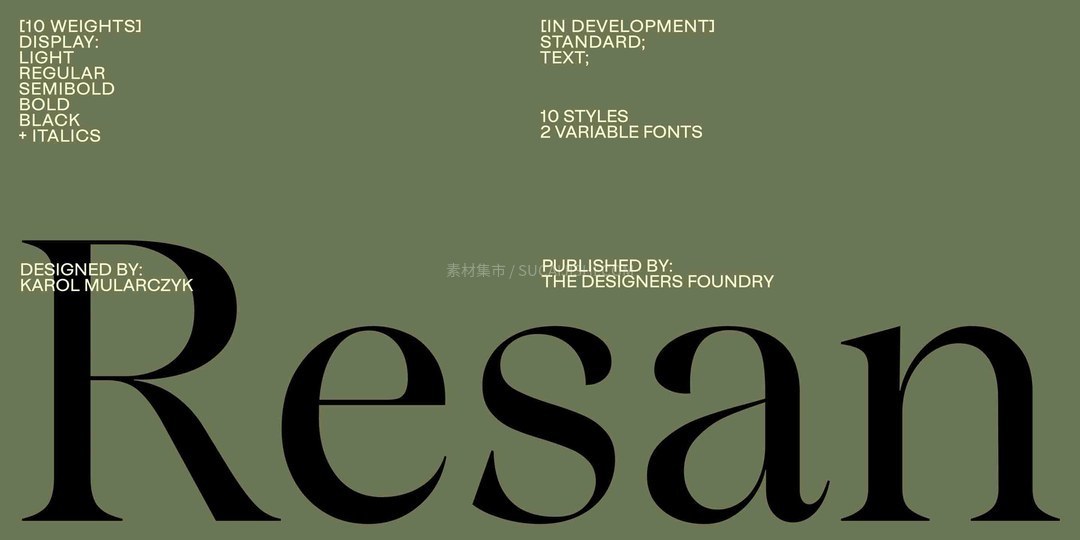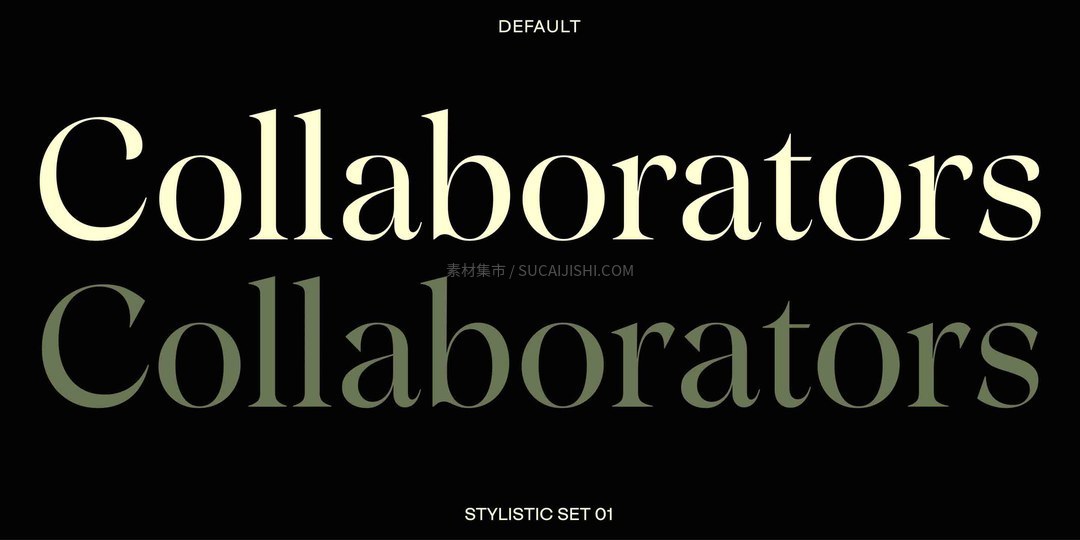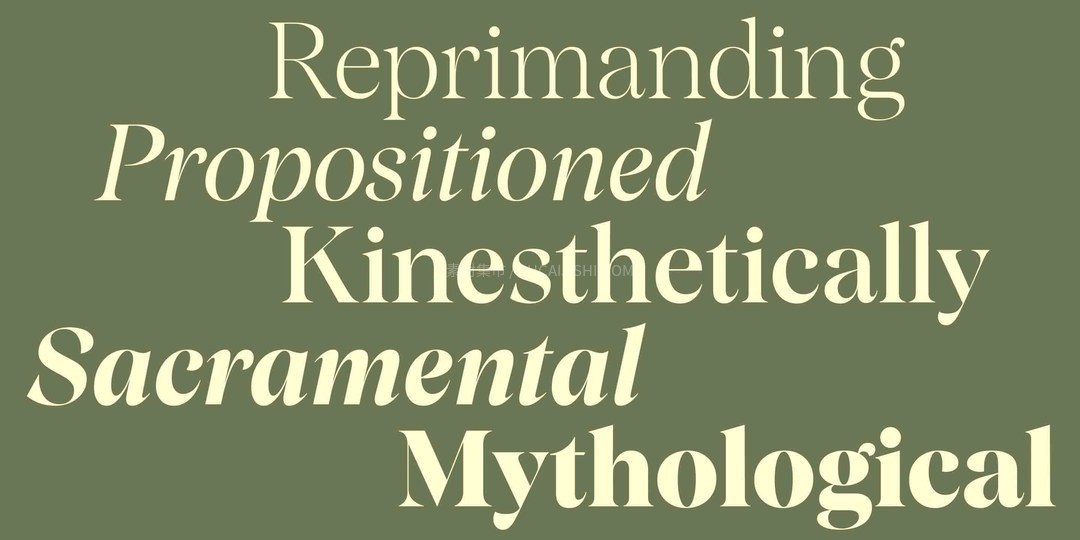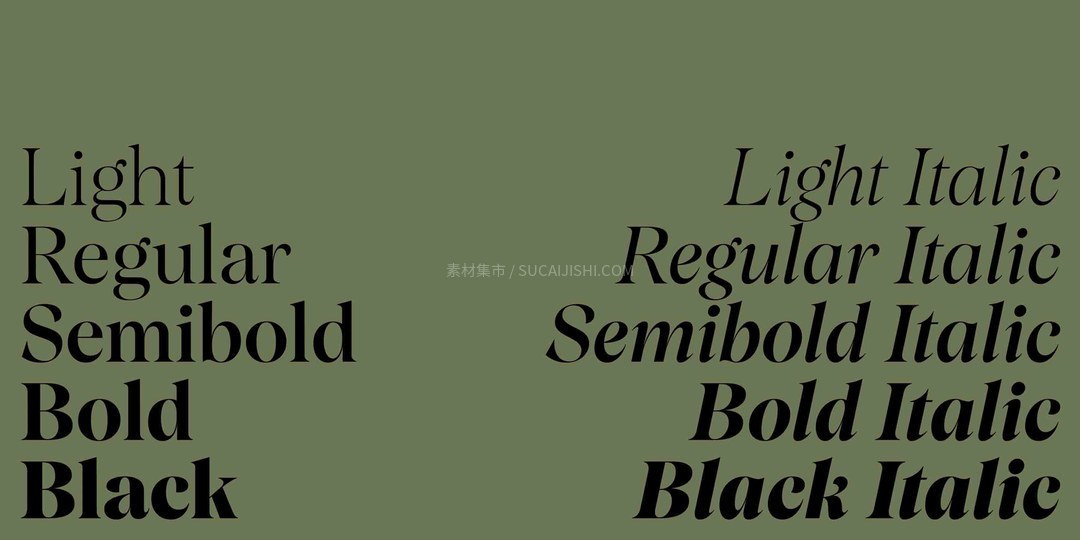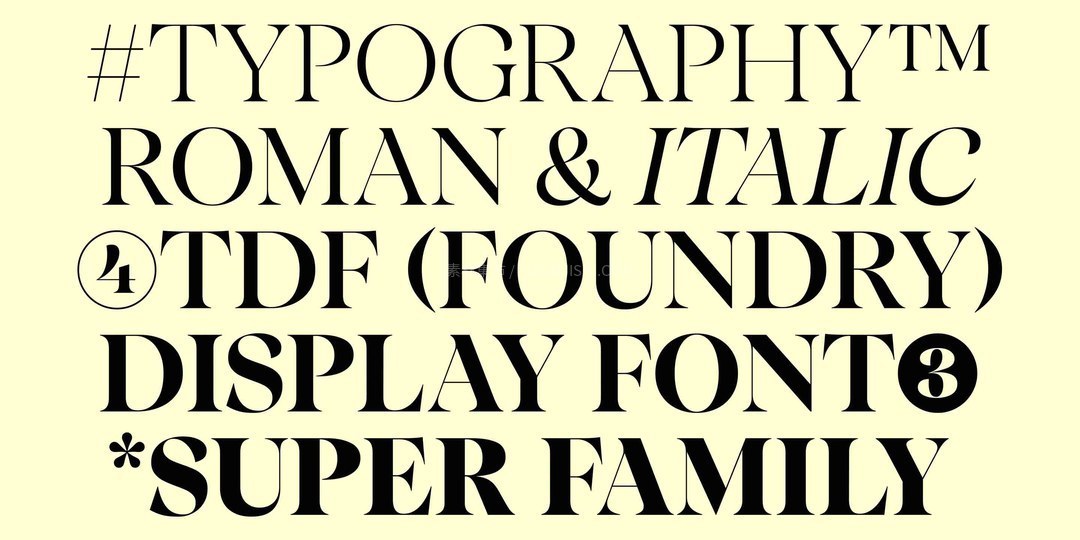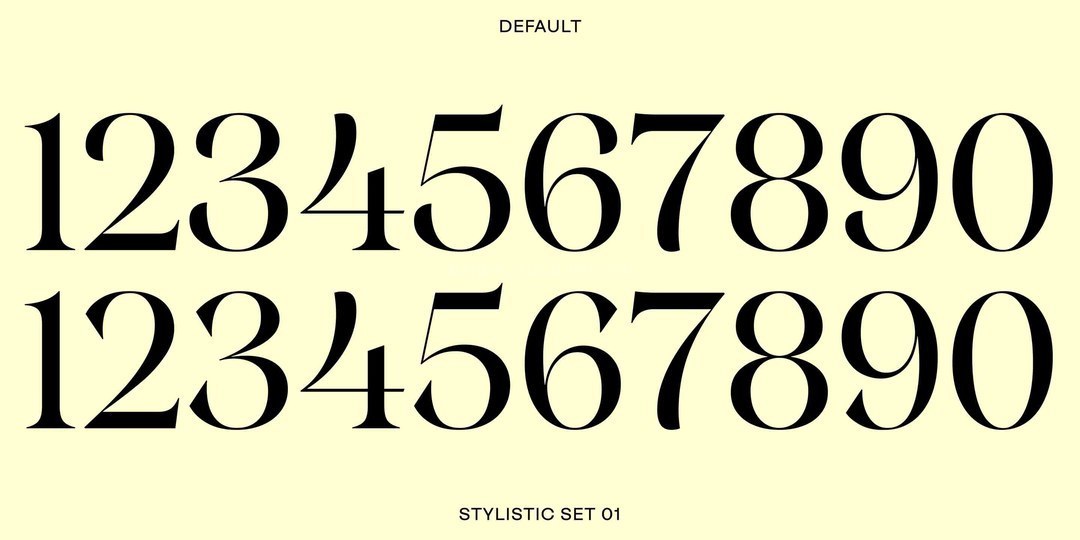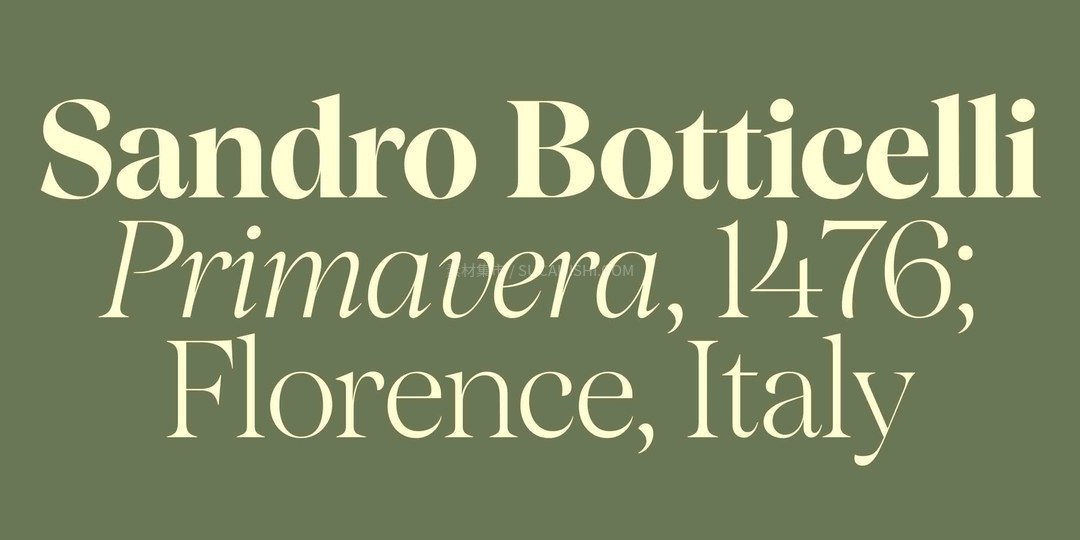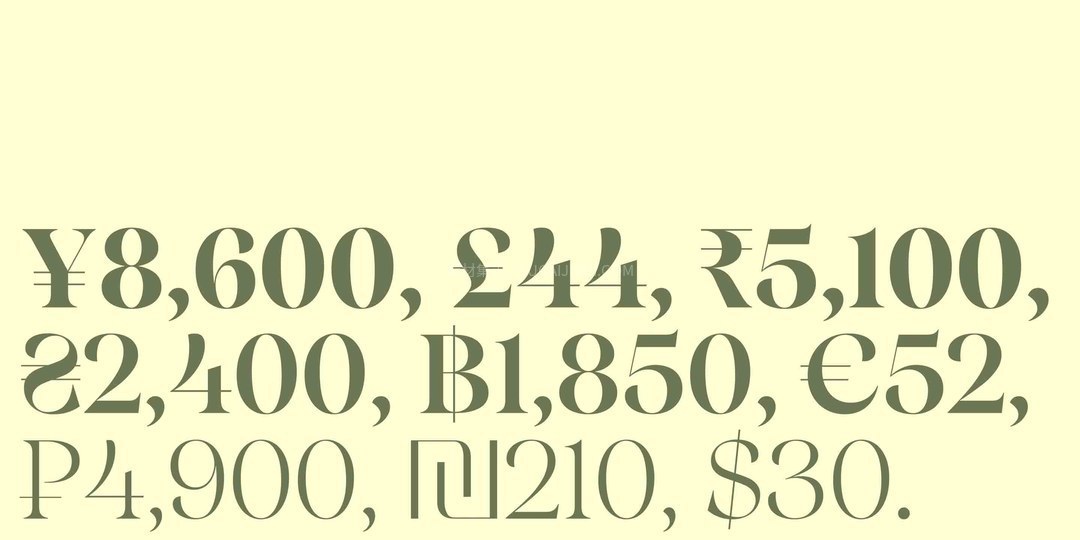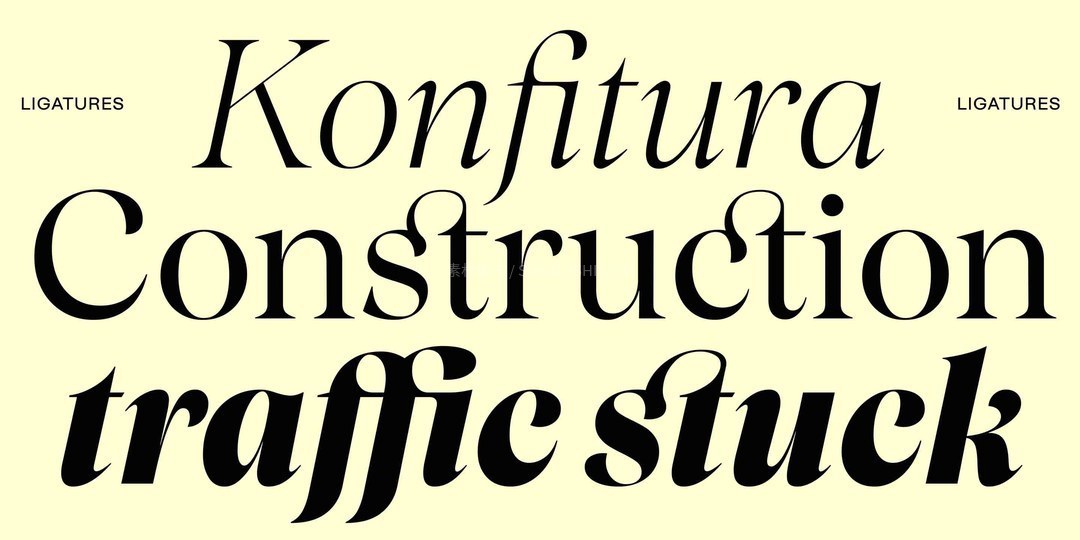
Resan Display过渡衬线展示字体家族
Resan 字体汲取了 17 世纪和 18 世纪早期过渡字体的特征,将自然的温暖和永恒的优雅融入精准规整的设计之中。鲜明的节奏、宽阔的比例和精细的切割细节,使其在标题尺寸下呈现出强烈的视觉冲击力,同时又保持了长篇文本排版所需的清晰度和沉稳感。此外,该字体还提供了样式集,允许您更改字尾形状,从而显著改变字体的整体感觉和氛围。这套系列包含 20 种样式及 2 种可变字体,支持上百种语言,非常适合用于高级标题排版、品牌视觉及展示设计。